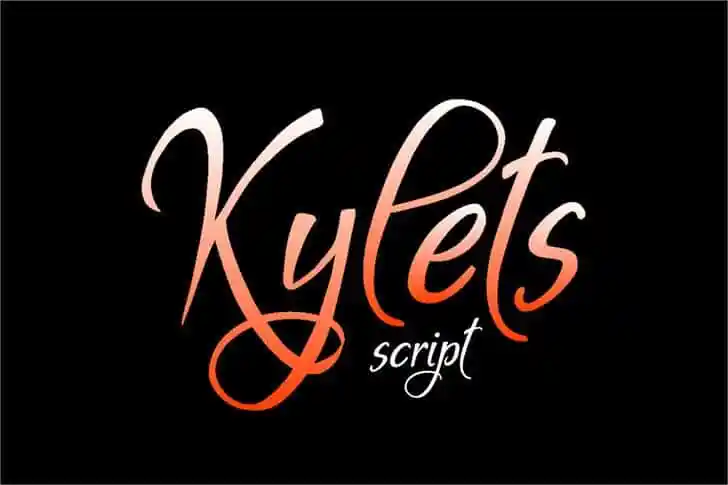
A Kylets Script Font é uma escolha perfeita para designers que valorizam a elegância das letras à mão, mas não querem recorrer a fontes tradicionais ou digitais. Introduzida pelo designer Eva Barabasne Olasz, essa fonte foi criada a partir da arte de escrever manualmente, transformando o estilo delicado e fluido dos traços em uma ferramenta versátil para criar designs sofisticados. Suas linhas onduladas e as opções de swashes inicial e terminal tornam-a perfeita para aplicar em projetos como invitations, logos ou qualquer outro projeto especial. Seja para um evento memorável, uma marca inovadora ou simplesmente algo que exalte sua personalidade única, Kylets Script Font é a escolha certa. Combinada com o conhecido design de Eva Barabasne Olasz, esta fonte oferece um toque artesanal e moderno ao seu trabalho.